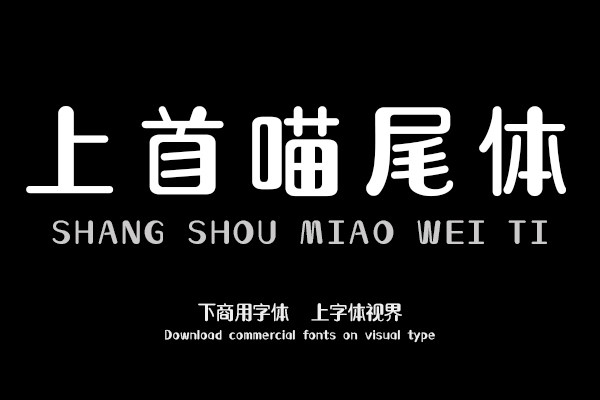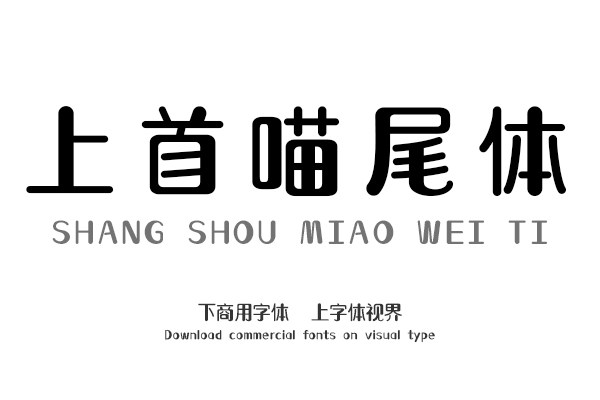
上首喵尾体,简体中文约6763字,字体笔画粗细对比明显,大体粗细交错,字体勾角处设有猫尾的特征。整体体型圆润可爱、赋有灵动性,适用于搭配在比较新颖、可爱、有特点......购买须知:“下载服务费”与“字体VIP”所获得字体 仅用于个人非商用, 商用请联系付费授权。本字体为电脑用字,手机没有root权限不支持直接手机换字(手机如何root,请自行百度搜索教程)。购买前请先 了解清楚后再付款 ,字体为虚拟产品无法回收 一旦购买不支持退款。